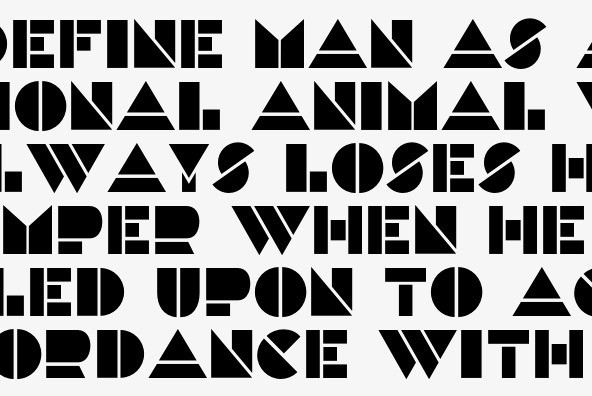
Вариативные шрифты | TypeType
Вариативные шрифты стали прорывом в шрифтовых технологиях! Теперь шрифтовой дизайнер может зашить в один шрифтовой файл несколько шрифтовых файлов и с помощью ползунков вариативности в режиме реального времени изменять настройки вариации шрифта. Вариативность может быть любой, начиная от традиционной вариативности по ширине, весу или наклону шрифта и заканчивая вариативностью, непосредственно влияющей на визуальный облик шрифта. Ещё одно преимущество вариативного формата шрифта, особенно если вы работаете с web typography, — небольшой вес шрифтового файла, по сравнению с весом традиционного шрифтового семейства.
На самом деле, возможности вариативности в шрифте безграничны и ограничены только вашей фантазией. Важно отметить, что на сегодняшний момент ещё не все оперативные системы, программы или браузеры поддерживают технологию вариативности, поэтому перед покупкой мы рекомендуем обязательно проверять, насколько ваше ПО поддерживает вариативные шрифты.
В библиотеку TypeType уже входит 17 вариативных шрифтов на любой вкус и под любую задачу. Вариативные шрифты из библиотеки TypeType можно разделить на четыре большие группы:
• ультимативные вариативные рабочие лошадки с тремя осями вариативности;
• шрифты с двумя осями вариативности;
• простые вариативные шрифты с 1 осью вариативности;
• вариативные шрифты, влияющие непосредственно на дизайн шрифта.
К первой группе можно отнести TT Commons™ Pro Variable, TT Lakes Neue Variable, TT Octosquares Variable, TT Supermolot Neue Variableь. У всех этих шрифтов вариативность регулируется по трём осям (толщина, ширина и наклон), благодаря чему пользователь получает широкую палитру выбора и возможность настроить ползунки так, чтобы создать уникальное сочетание.
Ко второй группе относятся шрифты с двумя осями вариативности, такие как TT Hoves Variable, TT Fors Variable и TT Autonomous Variable.
В отличие от первой группы, эти шрифты не позволяют работать с осью ширины, так как имеют только одну дефолтную ширину, но при этом они дают полную свободу (ограниченную лишь крайними значениями) в настройке толщины шрифта, его наклона или комбинации обоих значений.
К третьей группе шрифтов относятся шрифты с одной осью вариативности. Для каждой из осей есть отдельный шрифтовой файл. К таким шрифтам относятся TT Globs Variable, TT Autonomous Mono Variable, TT Ramillas Variable, TT Runs Variable, TT Interphases Mono Variable, TT Trailers Variable, TT Norms® Pro Variable, TT Firs Neue Variable. При работе со шрифтами этой группы у вас есть определённая свобода в выборе одного из параметров (ширины или толщины), что в свою очередь позволяет настроить шрифт под ваши задачи.
Самой необычной является четвёртая группа вариативных шрифтов от TypeType, к которой относятся TT Alientz, TT Frantz и TT Geekette. Основное отличие этой группы заключается в том, что вариативность влияет непосредственно на дизайн самого шрифта.
Например, в TT Frantz с помощью ползунка вариативности можно поменять среднюю линию шрифта: от очень высокого артнувошного вида до низкого и немного авангардного. Вариативность в TT Alientz позволяет трансформировать стиль шрифта от яркого и акцидентного гротеска в сторону очень колючей и характерной антиквы. А шрифт TT Geekette может трансформироваться от монолинейного слаба в пластичный слаб с обратным контрастом.
Шрифт должен быть функциональным и легко читаемым; это невидимый носитель информации, он воздействует исподволь, как экспертные советы при президенте влияют на принятие государственных решений, оставаясь в тени.
Сегодня теоретики признают собственную несостоятельность как создателей шрифтов, а практики — выбрасывают любимые учебники. Использование шрифтов носит сейчас гораздо более эклектичный характер, чем за все время, прошедшее с 1880 года. Внедрение новой наборной технологии повлекло за собой лавинообразное применение в произведениях печати экспериментальных и орнаментированных деревянных шрифтов.
Вычислительная мощь существующих на сегодняшний день настольных компьютеров открыла простор для творчества в создании шрифтов. Рисунки, делавшиеся быстро и интерактивно, более непосредственно передают реакцию дизайнеров на окружающий их мир, подобно тому, как рэп-музыканты с помощью музыки выражают свое неприятие урбанистической жизни.
В ответ на безликость информационной эры 90-х годов 20-го века многие авангардные шрифты все больше начинают отражать человеческие эмоции и характер текстового сообщения — резкого, искреннего или эксцентричного, — не просто передают содержание, а сами становятся его частью.
Шрифты через года
ITC Avant Garde Condensed Bold